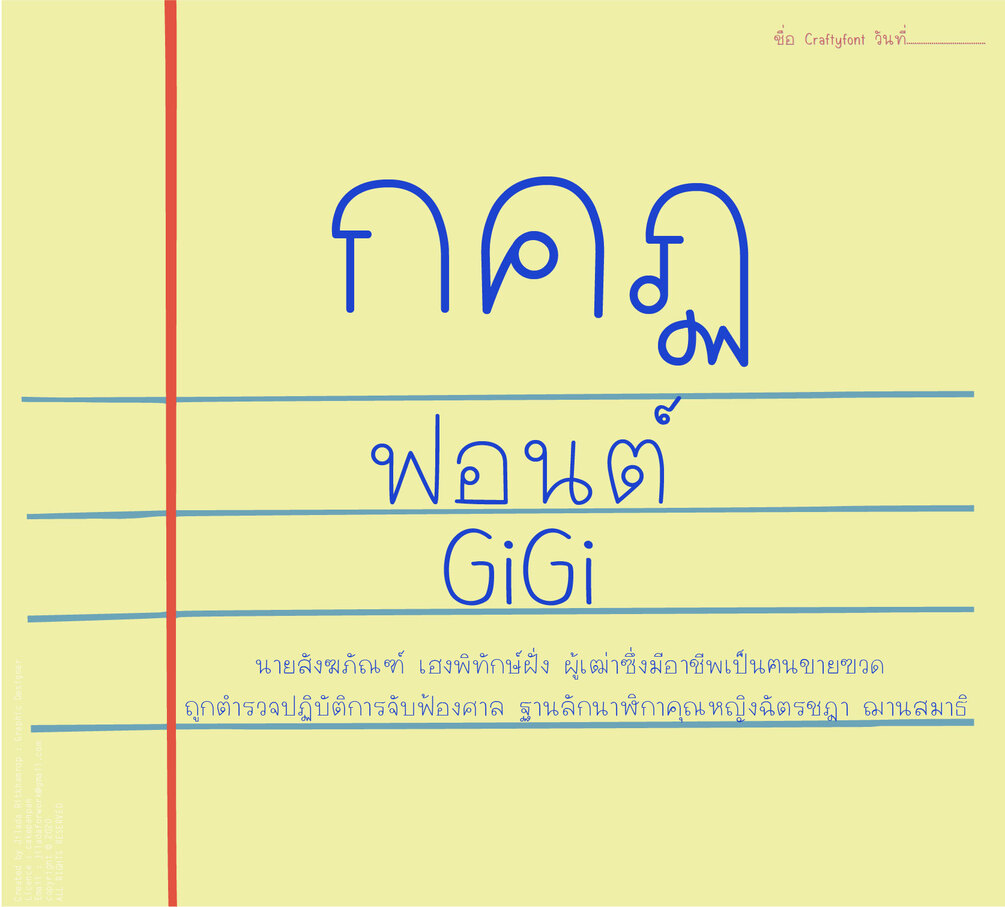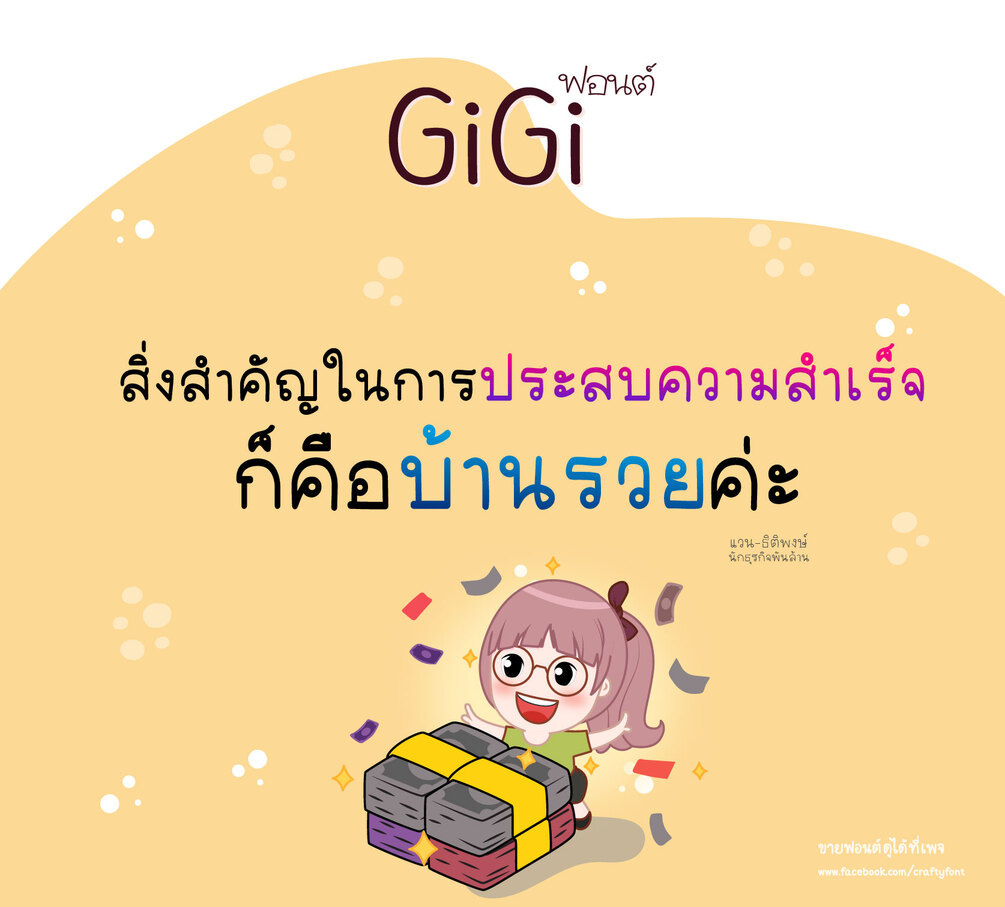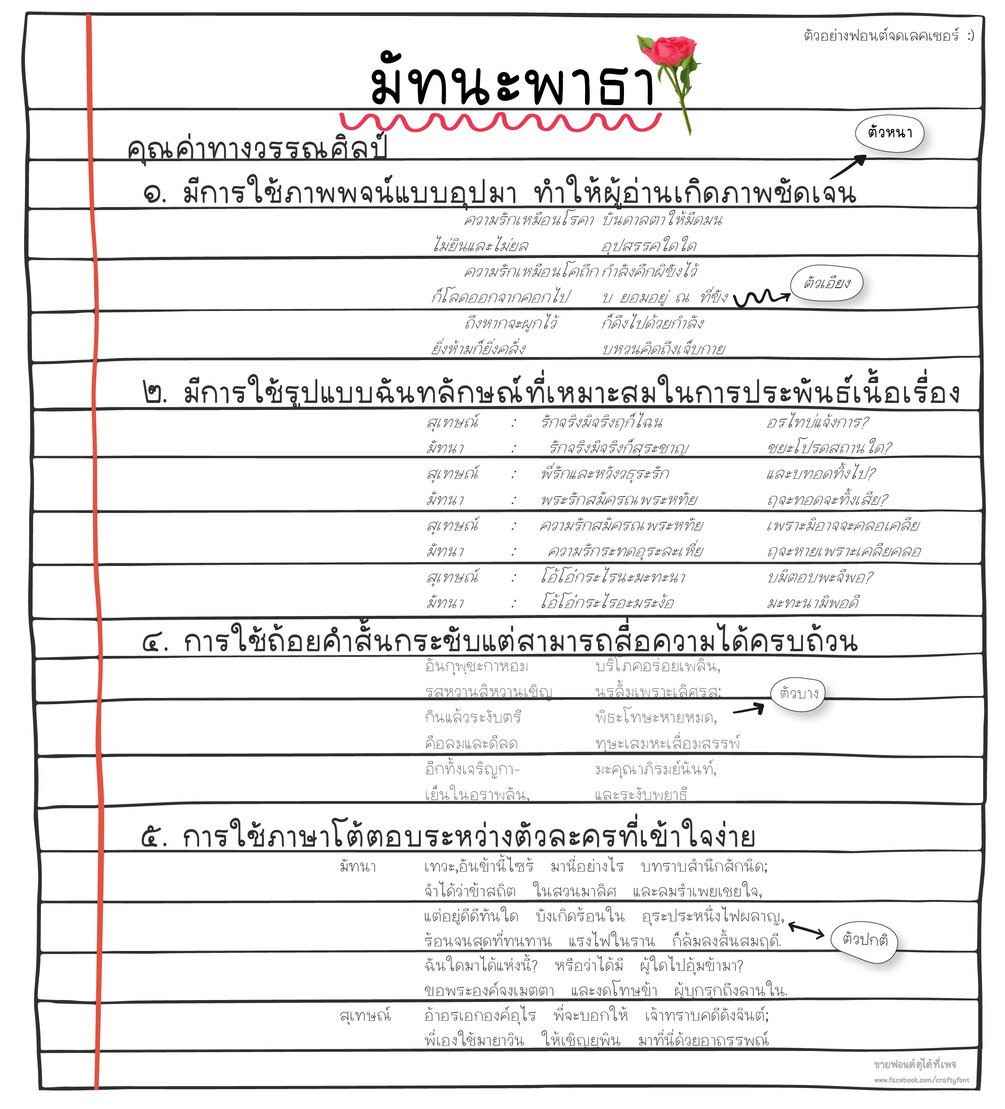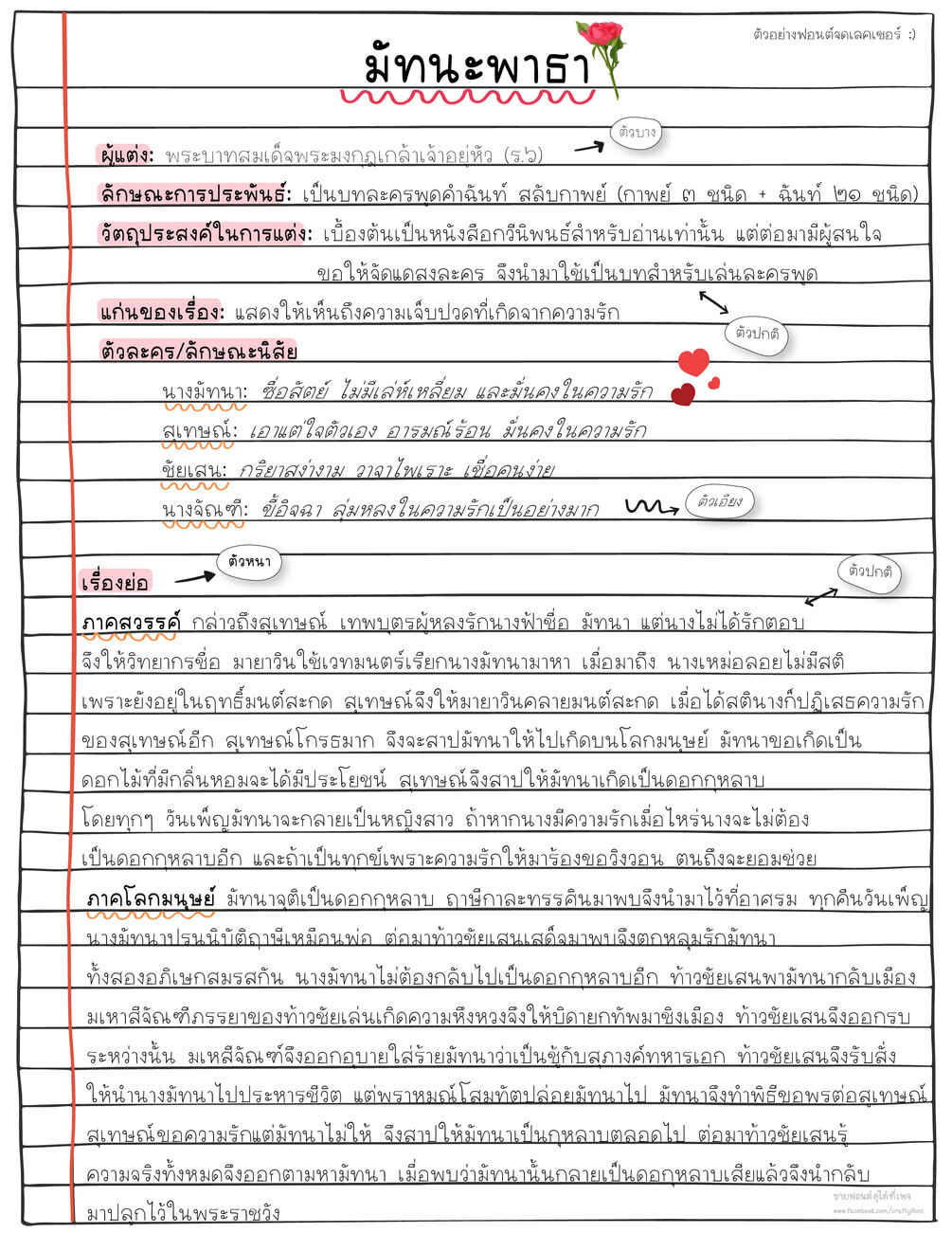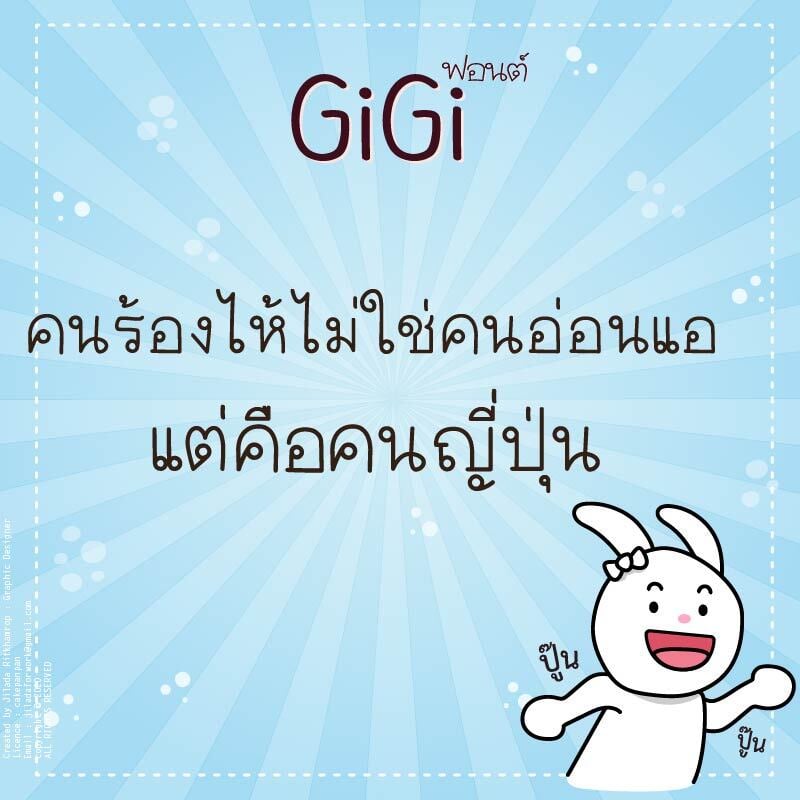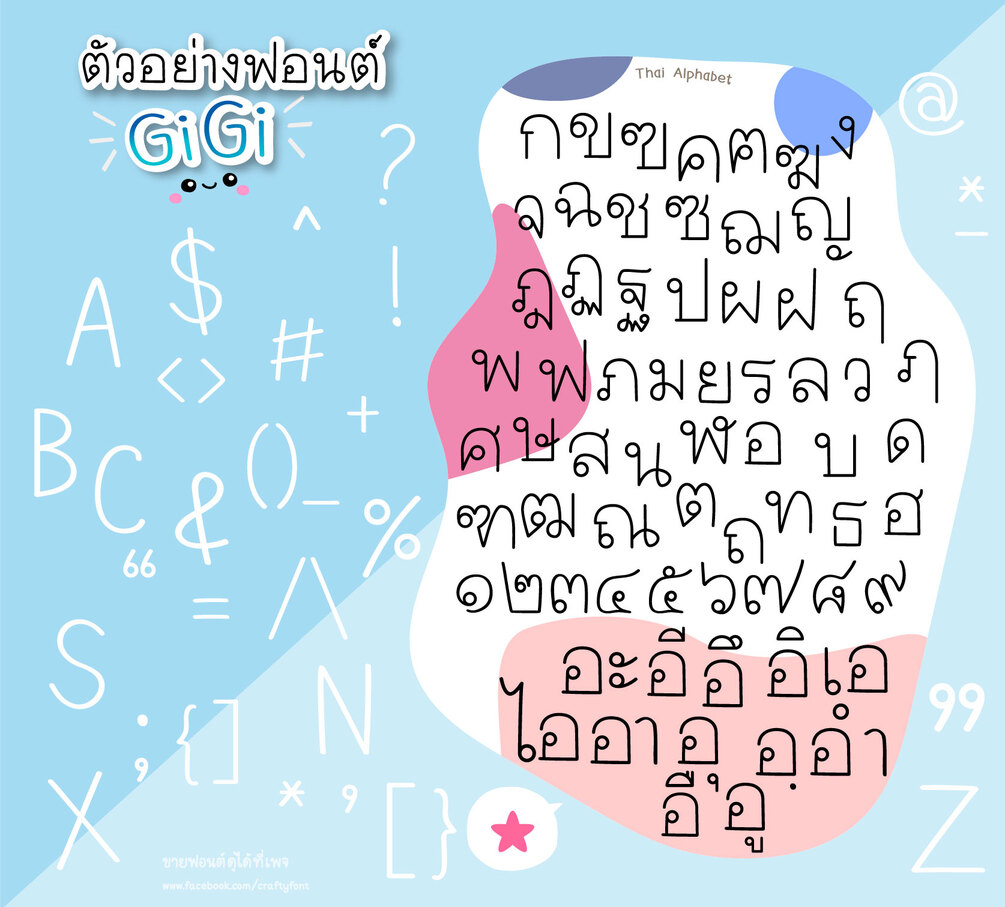
GiGi Font (ฟอนต์กีกี้)
ฟอนต์สำหรับเลกเชอร์น่ารักๆ ในอาณาจักร crafty font มาอีกแล้ววว 🥰🥰
ฟอนต์ตัวนี้มี 4 น้ำหนักด้วยกัน ตัวบาง ตัวเอียง ตัวหนา และตัวปกติ